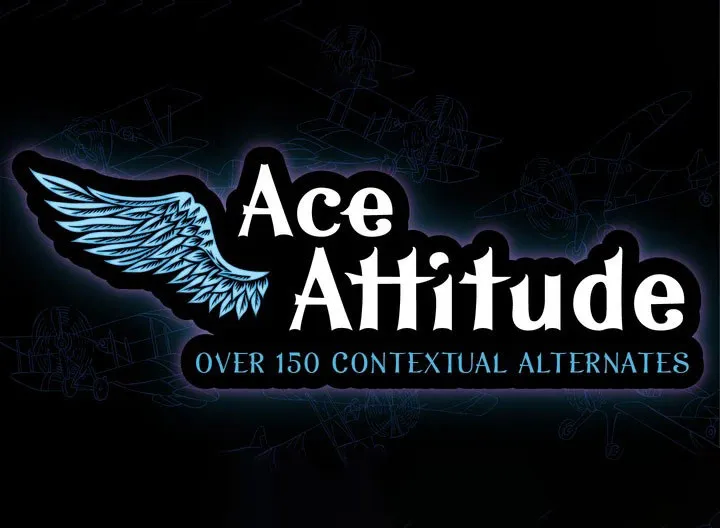
Ace Attitude Font Demo
A ‘Ace Attitude Font Demo’ é uma escolha perfeita para criar identidades visuais robustas e modernas. Com um estilo de tipo que abraça a simplicidade, ela traz um toque pragmático sem perder o ar sofisticado. Esta fonte é ideal tanto para logotipos e marcas quanto para ambientes publicitários onde deseja chamar atenção, como revistas, panfletos, embalagens ou outdoors. Com sua estrutura clara e moderna, a ‘Ace Attitude Font Demo’ se adapta perfeitamente a uma variedade de aplicações, tornando-a uma fonte imprescindível para designers em busca de um estilo que expressa determinação e confiança. Sua versatilidade faz dela uma opção segura para qualquer projeto visual que busque um destaque impressionante.